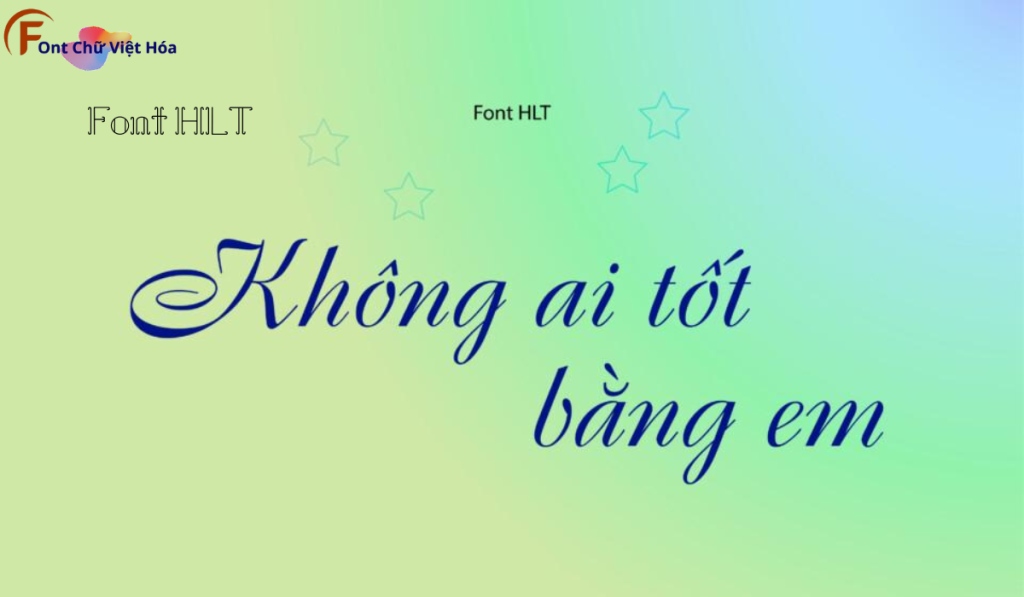
Font HLT Boulevard Việt Hóa
Tác giả: HLT
Bộ Font: HLT
Font HLT Boulevard Việt Hóa là một font chữ không chân cá tính, thuộc bộ font HLT. Được thiết kế với mục tiêu mang lại sự hiện đại và tinh tế, font này phù hợp cho các dự án thiết kế như poster, banner, và website. Với các nét chữ rõ ràng và độ dày đều đặn, Font HLT Boulevard Việt Hóa không chỉ dễ đọc mà còn tạo cảm giác chuyên nghiệp.